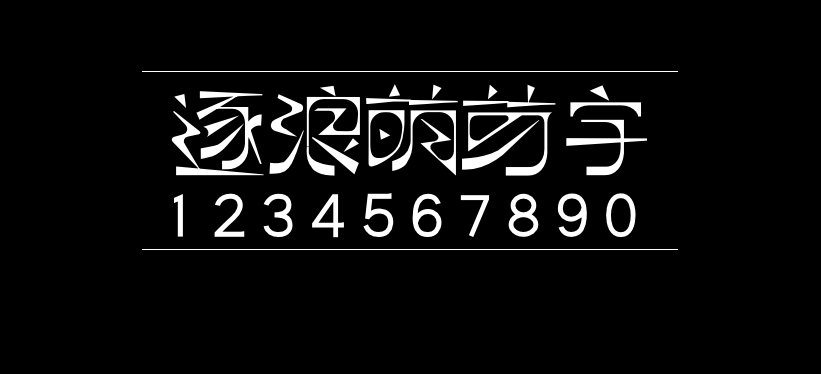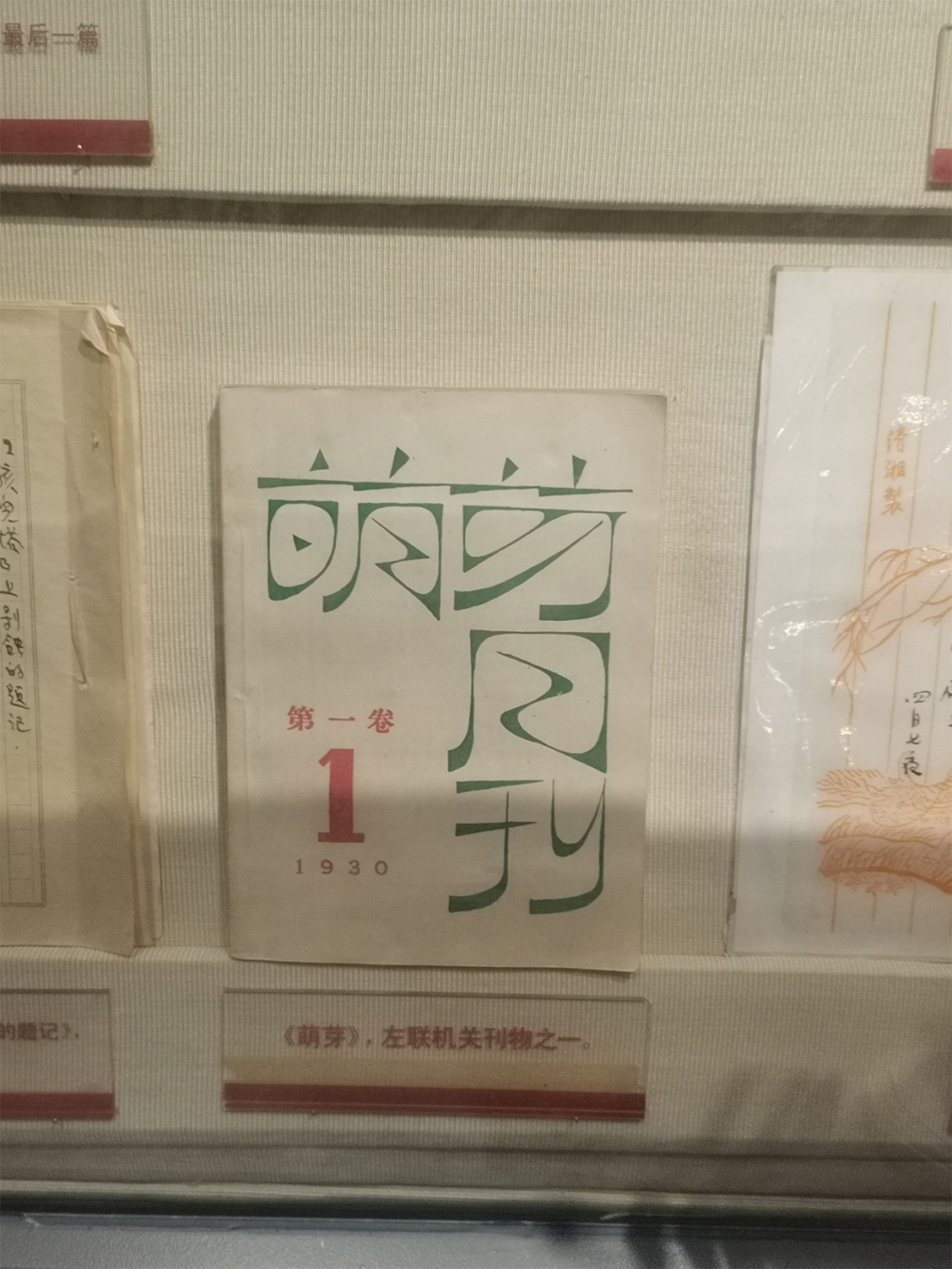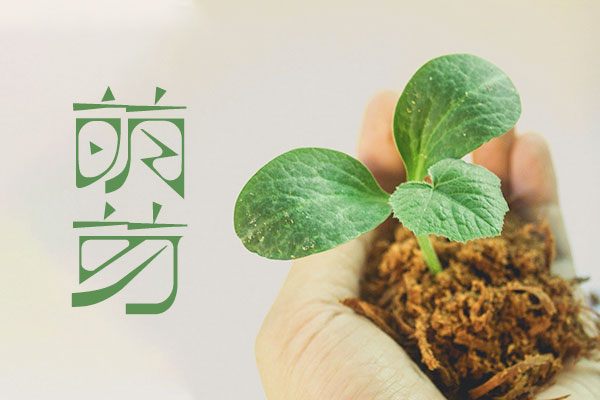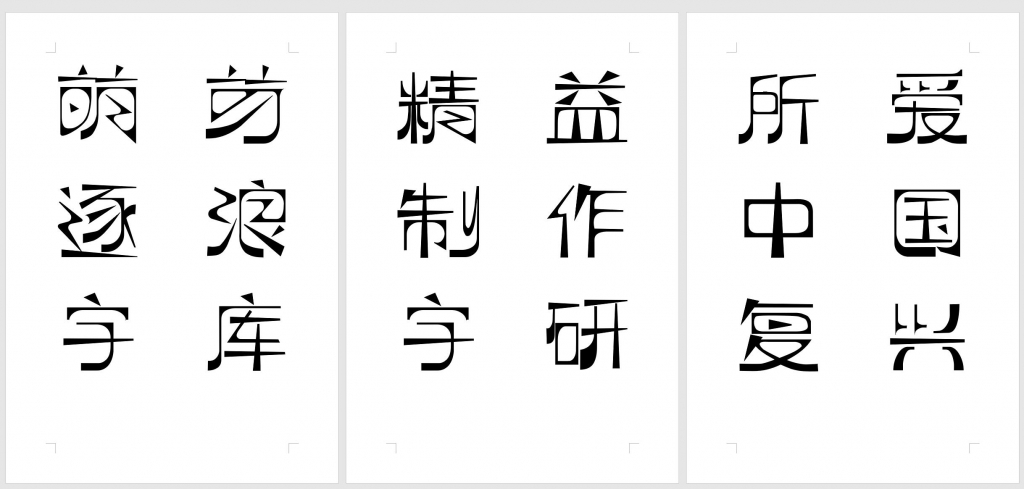
逐浪萌芽字
逐浪萌芽字(Zoomla CMS Fonts)是一款参照近代中国共产党《萌芽》月刊的艺术字体。,源自五四运动文化,力求体现近代文艺风。
字体线条呈现外方内圆格局,有尖锐的外角、三角部件,而内部空间则呈现圆形切割效果。 这体现了五四、清末民初,在工业革命思维冲击下,一代文化人对于中国汉字的探索。 又似布尔什维克人的工人、工业文化在汉字下的体现。
尖锐、锐角三角形的部件,从中体现了上进、革命、进击。
结字扁形,即左右宽度大于上下高度。
1.外角采用尖角,内角采用弧角
2.是一个抽象的孤形字。
3.试图创造上个世纪30年代“左联”的手写字体风格,该风格是用于出版物出版,简朴又不失艺术性。
4.多弧形、多三角形。
5.整体偏矮宽方正型,非常规字体,异型字居多
6.笔画粗细对比明显,角的笔画相对横竖线要粗
7.竖线笔画下端粗上端细,横线笔画左边粗右边细
8.外角整体偏方形,内角整体偏圆形的创意字体
9.整体风格硬朗纤细
逐浪萌芽字逐浪萌芽字已包含国标规定的简体6763字,简体字还是非常全的。而繁体字的支持则相对弱一些。